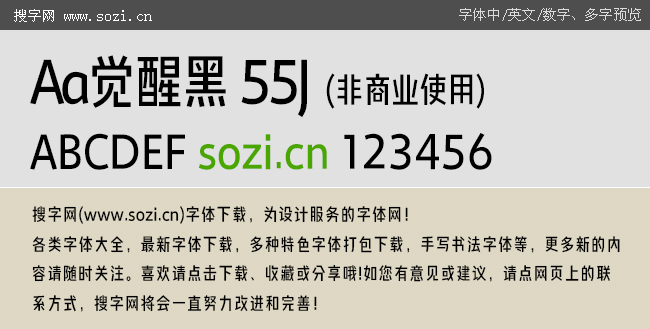
Aa觉醒黑 55J
搜字网给大家提供一款Aa觉醒黑 55J(非商业使用)中文字体下载,Aa觉醒黑是一款艺术黑体字体,字体简洁大方,字形端正耐看,具有很好的视觉感,适合应用于艺术设计、平面宣传设计、网页设计、海报设计等应用(此字体为个人非商用版,商用可以联系QQ:1006760504)。
• 风格类别: 现代艺术体